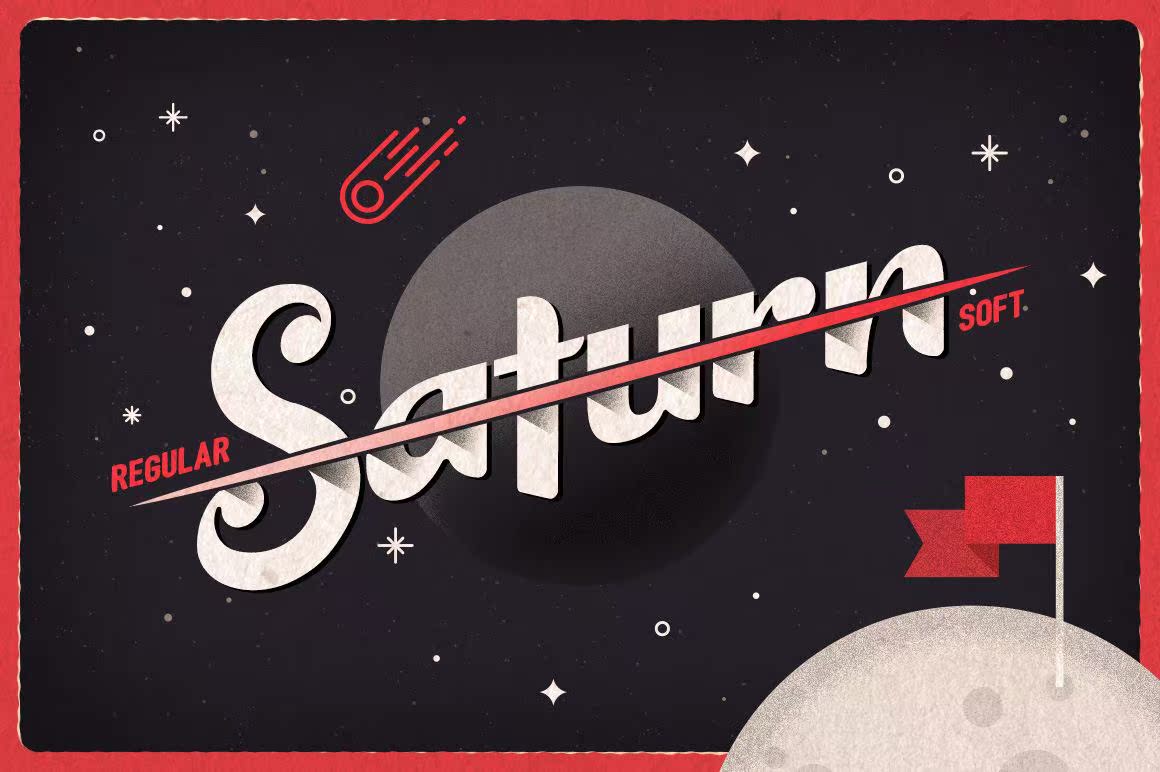
受VintageMagazine和旧电影的启发。Hars包括大写、小写、数字、标点符号、货币符号和每个字符的许多变化,包括五字替换和常用连字。还支持使用上下文替换,替换字符将自动生成每个最终字符,当输入单词时。Harson完善为使用徽标,信头、海报、装置标志、Labeladetc。灵感来源于VintageMagazine和旧电影。大写字母、小写字母、数字、标点符号、货币符号和每个字符的许多变化,包括五字替换,和通用连字。还支持使用上下文替换替换字符,这些替换字符将自动生成所有最终字符。Harson可完美地用于标识、信头、海报、装置标志、Labelandec。